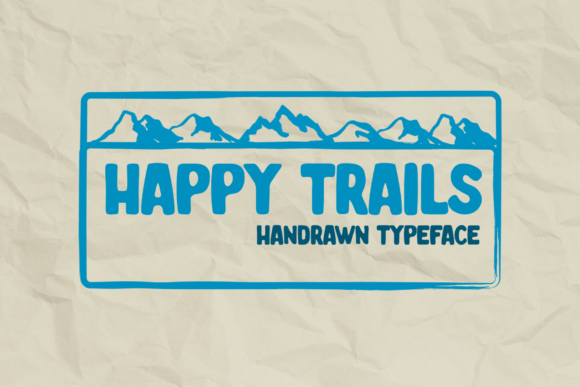
Happy Trails
適切なデザイン要素を見つけるのは難しい場合がありますが、Happy Trailsは作品を即座に引き立てる優れたコレクションを提供します。
POD(オンデマンド印刷)製品、結婚式の招待状、またはソーシャルメディアのグラフィックを作成している場合でも、Happy Trailsは理想的です。